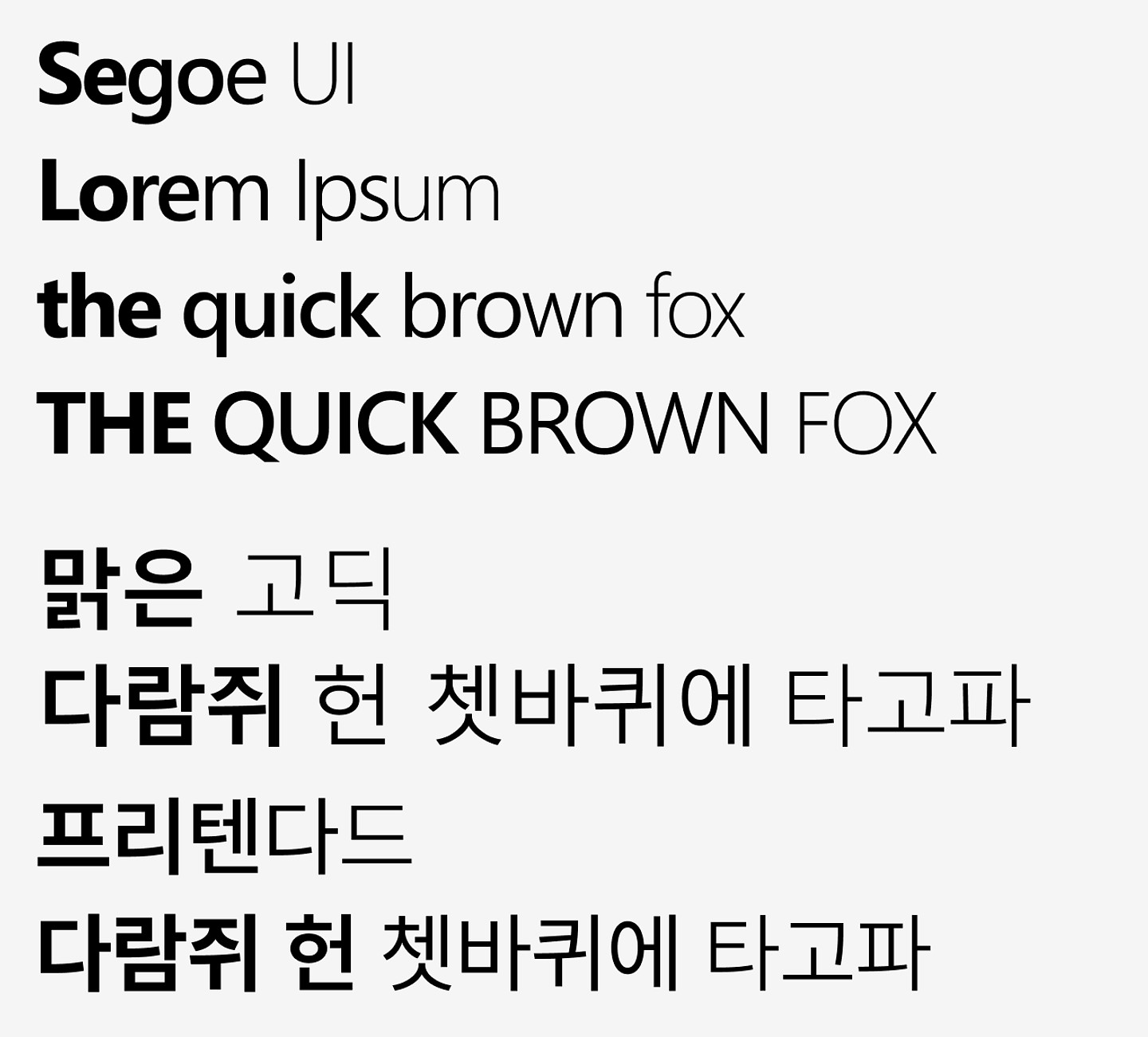
Segoe UI, 맑은 고딕과 비슷한 폰트를 찾습니다! 😃😃😃😃😃😃 안녕하세요. UXUI 디자인을 독학하고 있는 컴공과 학생입니다. 그동안 프리텐다드, NotoSans, 본고딕, SUIT 등을 사용하다가,, 이제는 좀 질리기도 했고, 여기저기에서 너무 많이 쓰이는것 같아서, 최근 주목받고 앞으로 많이 재해석되어 많이 쓰일 '프루티거 에어로'를 구현하고자 하고 있습니다. 문제는 프루티거 에어로에 적합한 타이포인데요,, 프루티거 에어로라면, Microsoft가 2004-2013 년 시기에 만든 윈도우 비스타의 디자인이 가장 대표적이라서, 이 시기에 MS가 사용한 Segoe UI와 맑은 고딕 폰트를 좀 찾고 있는데, 이게 구글에서 찾아봐도 쉽게 나오지 않네요. ⠀ Segoe 폰트가 매력적인 이유가 p, q, o, l 등 기다란 타이포들이 미학적인건데, Noto Sans 등은 그렇지 않구요. 맑은 고딕도 마찬가지로,, 프리텐다드나 여타 폰트는 맑은 고딕 만큼 깨끗한(?) 느낌을 주지는 않는것 같구요. ⠀ 어렵네요.. 혹시 비슷한 폰트가 있는지 여쭤보고자 합니다!